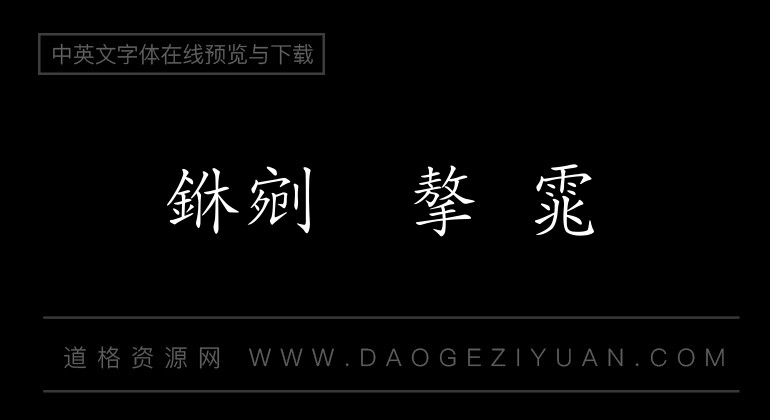
文鼎细楷是一款繁体字体,它源自于明朝细楷体,是一种经典的汉字字体。它的字形比较细小,曲线柔和,更加精致,更具有古典气质,可以用来创作书法、图案、排版等。文鼎细楷的笔画细腻,字形优美,适合用于宣传单、书籍、杂志等排版印刷,具有较强的古典气质和高贵的风格。文件名:WenDingXiKai-1.ttf
文鼎细楷是一款非常不错的手写艺术字体,具有很好的视觉感,适合于文化类的宣传设计、商业类品牌的广告和产品包装设计以及个性化文字排版等较多场景。